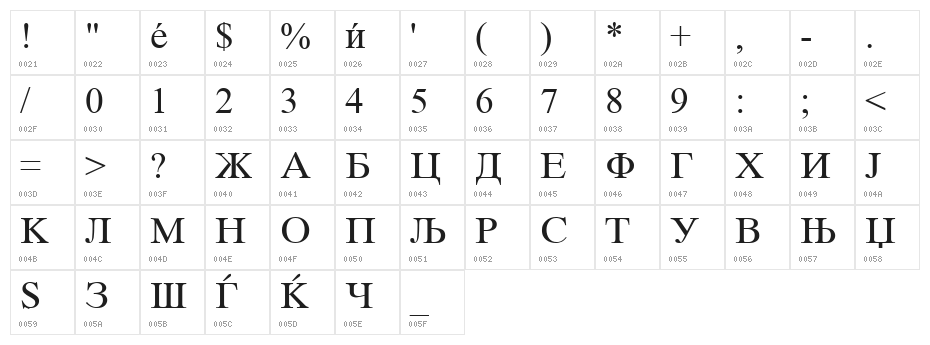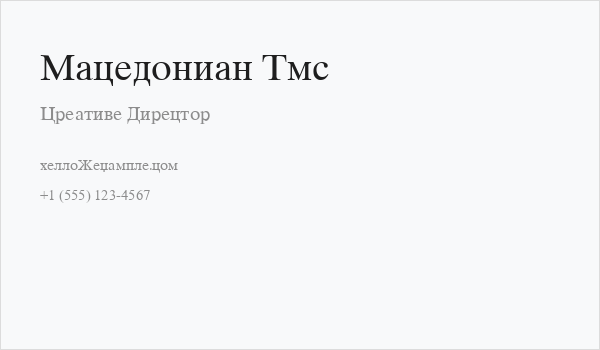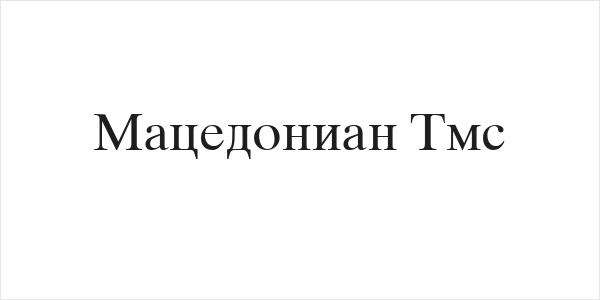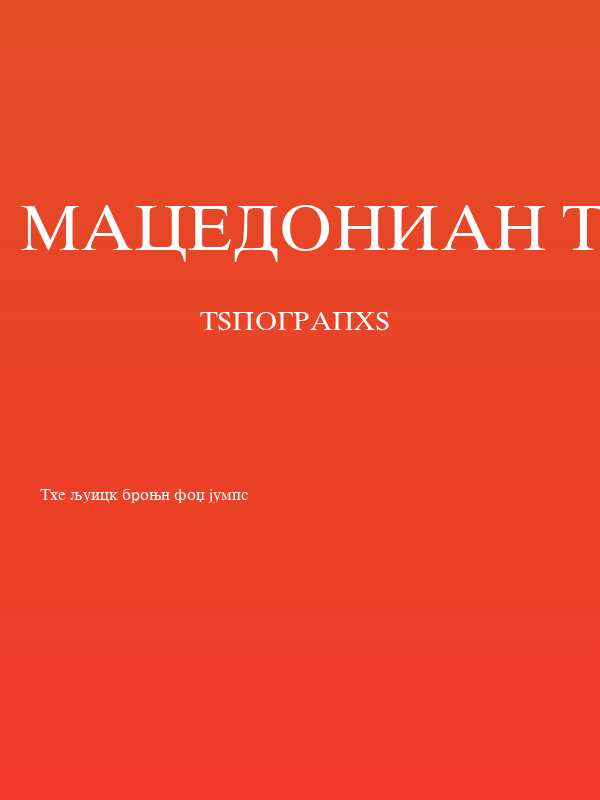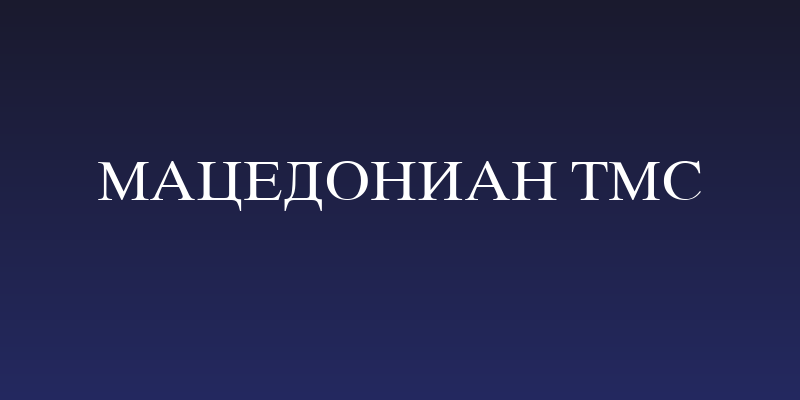
Macedonian Tms Font
✎ Serif
| Kategorien | Serif |
| Gesamtstil | Classic |
| Anwendungsfall | Headlines, Body text, Formal documents |
| Vorgeschlagene Projekte | Ideal for use in formal documents, book publishing, academic papers, and branding for traditional businesses. |